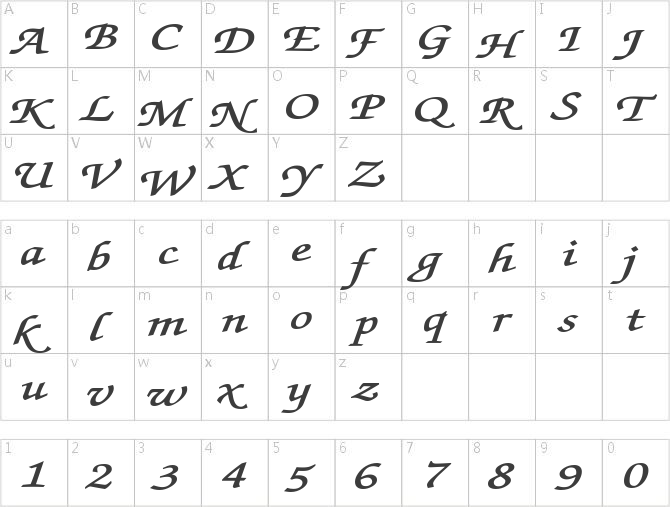
exchequerscriptextendedbold
exchequerscriptextendedbold字體字庫(kù)是一款讓人賞心悅目、百看不厭的英文字體,適合各類廣告和產(chǎn)品包裝設(shè)計(jì)應(yīng)用,字體大小0.05MB,格式為ttf字體,上傳用戶是浪跡天涯,作者/版權(quán)方為未知